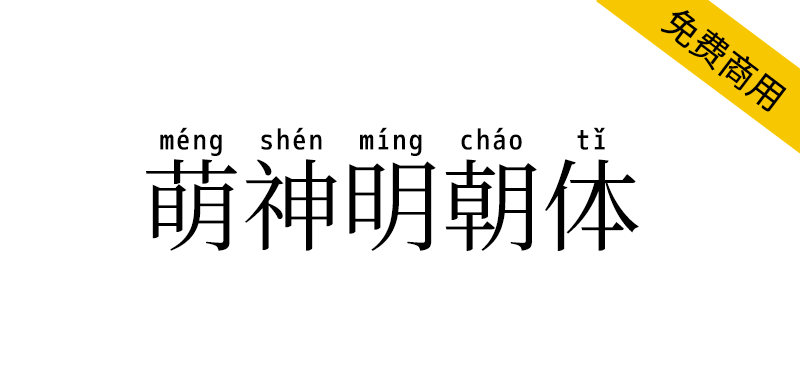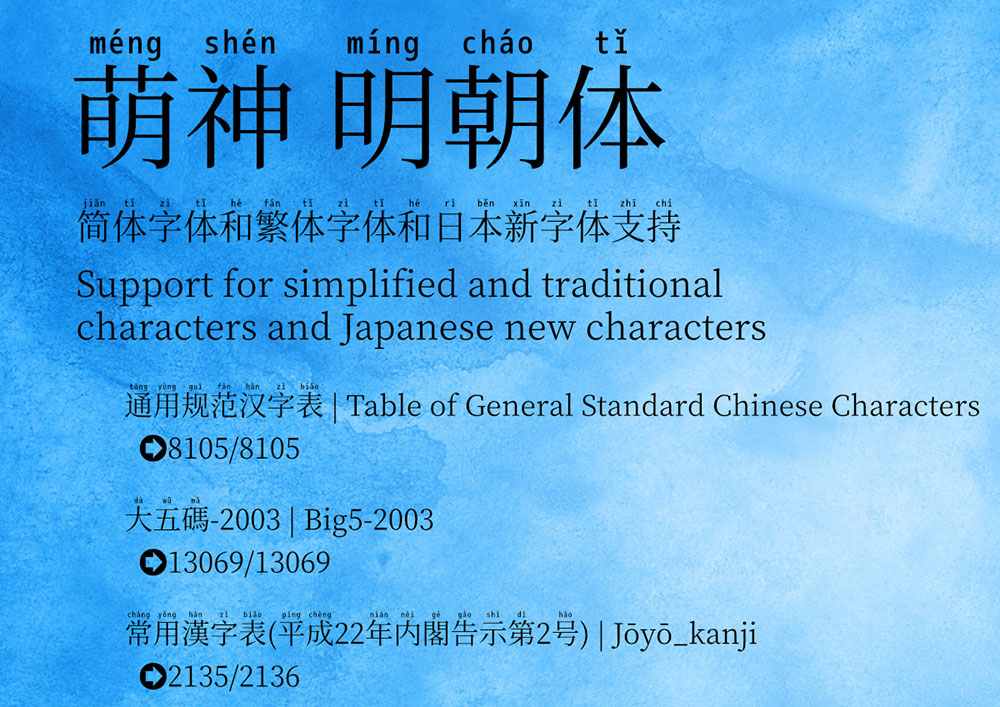
萌神明朝体是一款用于学习中国汉字的拼音字体,由思源宋体和M+ FONTS进行改造而成,采用SIL Open Font License 1.1授权协议发布的一款免费商用字体。 这是一款能够显示基础日语、简体中文及繁体中文的字体,并且专门为简体和繁体汉字均添加了拼音注音的字体设计,是一种用来帮助学生更快地学习和阅读汉语的字体,在某些设计场景其实也挺实用的,特别是对教育类的设计比较有用。
萌神明朝体实现了上下文替换(feature of“rclt”at GSUB)以支持多音字。另外,还可以使用Unicode IVS(表意文字变体选择器)来切换到不同的拼音。